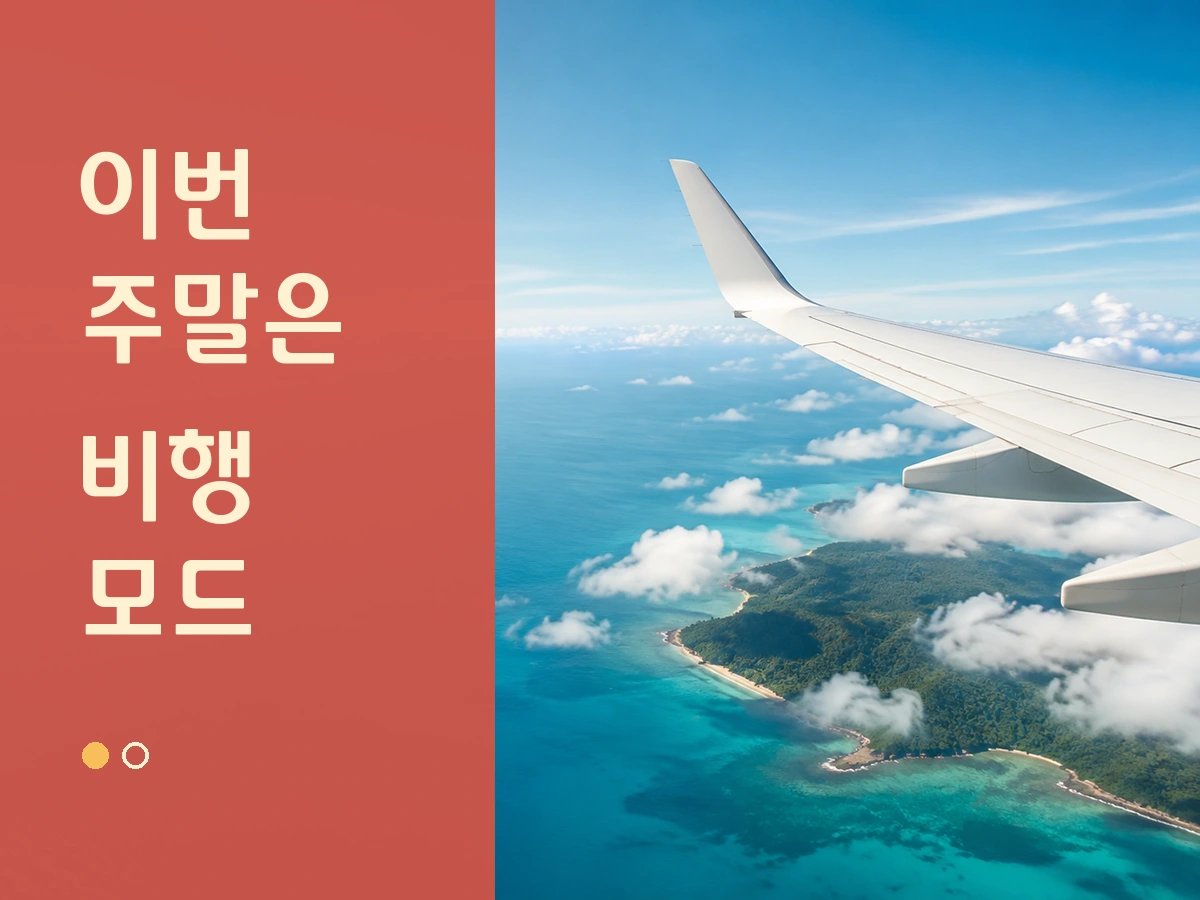
티웨이 항공체 — 티웨이 X 폰트랩(주)에서 배포하는 무료 폰트입니다. 정돈된 레트로 감성에 둥근 맺음과 꽉 찬 장방형 구조를 더한 고딕체
티웨이항공이 2021년 3월에 폰트랩과 함께 공개한 전용 서체로, 국내 항공사 가운데 처음으로 전용 서체를 무료 배포한 사례입니다. 항공체와 날다체, 하늘체 세 벌을 한꺼번에 내놓았고 각각 제목용과 브랜드용, 본문용을 맡습니다. 이 서체는 그중 제목 쪽입니다.
제작사가 밝힌 조형은 이렇습니다. 티웨이항공 CI를 기반으로 개발했고 잘 정돈된 레트로함과 부드러운 인상이 특징이며, 초성을 조금 크게 디자인해 전체적으로 흔들림 없이 꽉 짜인 장방형의 글자 구조를 만들었다는 것입니다. 초성을 키우는 것은 제목용 서체가 자주 쓰는 방법으로, 글자를 멀리서 봐도 알아보기 쉽게 만듭니다.